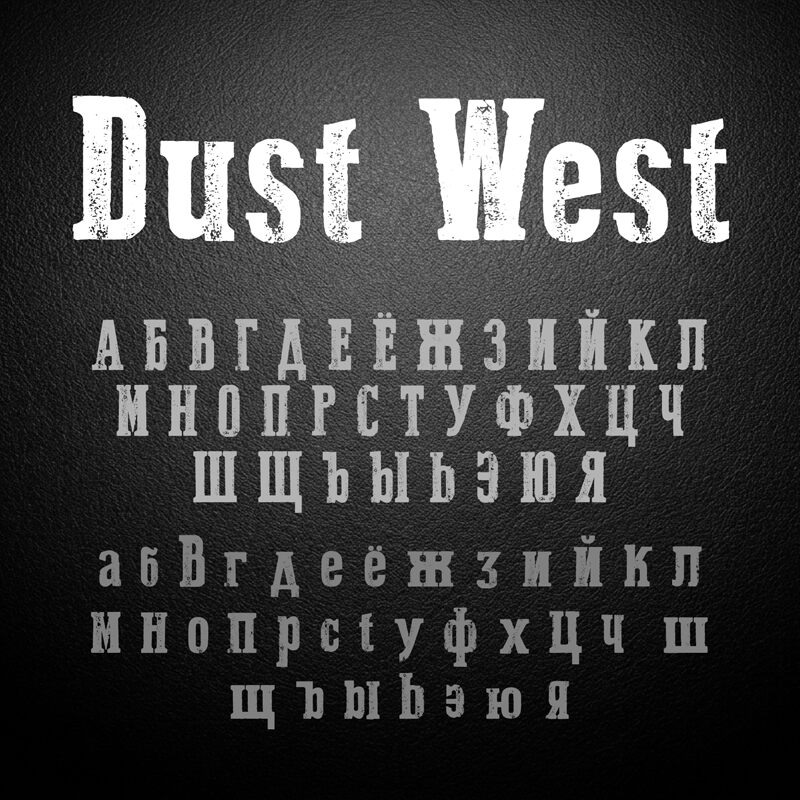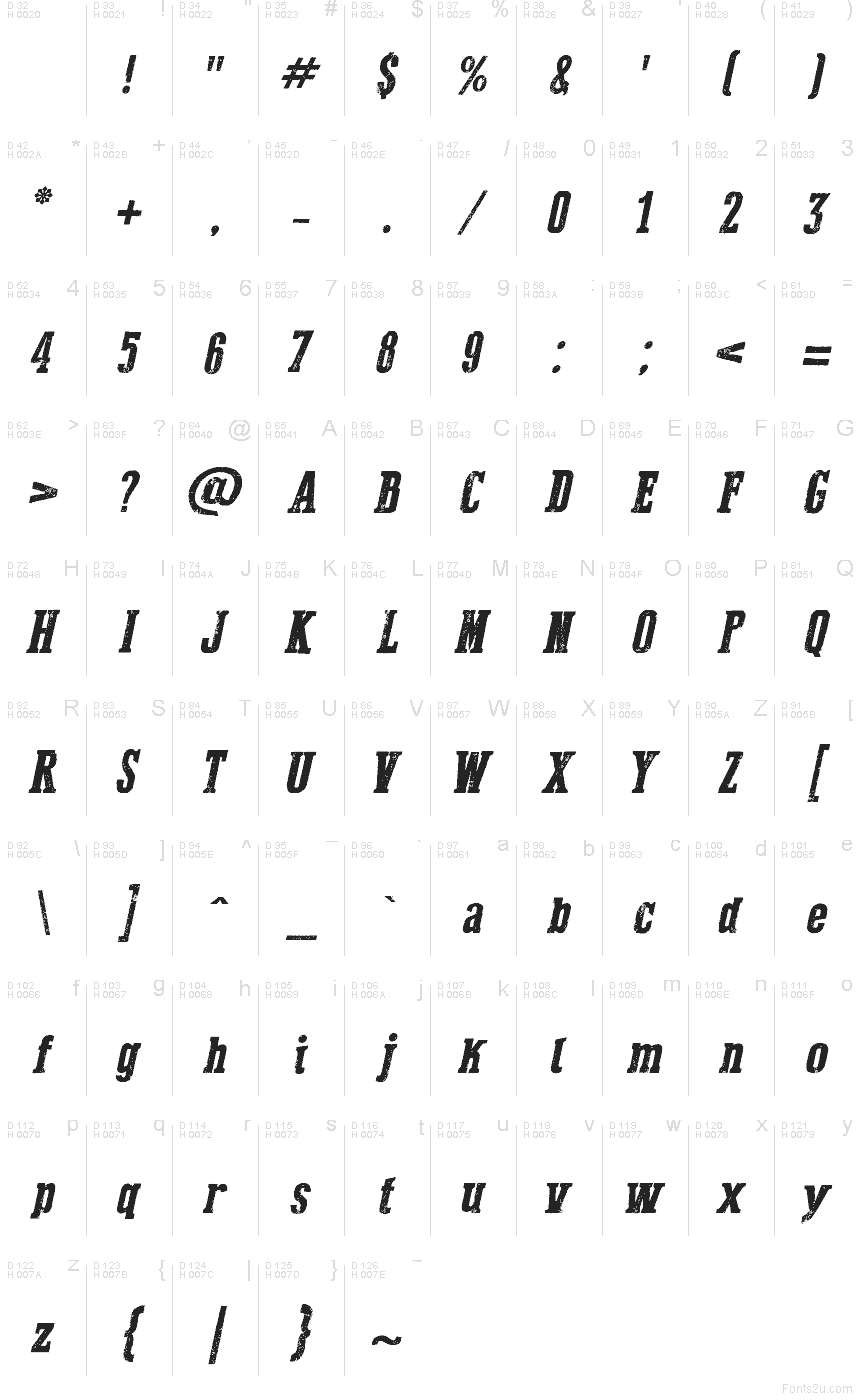
Dust West Italic
Dust West Italic od Galdino Otten je bezplatné westernové titulkové písmo s patinou, ktoré v sebe nesie drzosť starých plagátov z divokého západu a krčmových nápisov. Jeho šikmé písmená majú robustný, drevotlačový vzhľad, poznačený drsnými vrypmi, vďaka čomu celý font pôsobí zaprášene, obnosene a tak trochu divoko, určite nie úhľadne či prehnane nostalgicky.
Prirodzene zapadne do plagátov, brandingu pre whisky či barbecue, obalov albumov, letákov na akcie aj titulkov, ktoré potrebujú ten správne ošľahaný westernový nádych bez pocitu falošnosti. Ako bezplatné písmo sa hodí aj na krátke nadpisy, popisky a monogramy, kde šikmý sklon a zvetraná textúra hovoria za všetko.